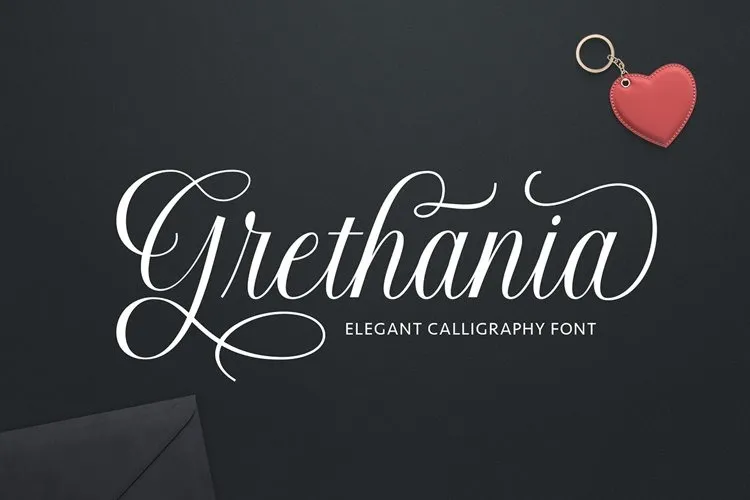
Grethania Font – Download Grátis
Grethania é uma nova fonte de corteleta elegante e moderna, perfeita para trabalhos formais que exigem tanto a elegância quanto a modernidade. Este script é um marco único no mundo das fuentes de calligrafia porque apresenta um estilo suave, limpo e feminino. Seu charme sensual e glamouroso faz com que seja uma escolha ideal para design em variados campos: desde cartões de convite e rótulos até logotipos, moda e estação de escrita; passando por românticas novelas, revistas e livros, cartões de congratulações ou casamentos e embalagens. A Grethania está concebida para se adaptar em qualquer situação formal do dia a dia, tornando-a uma fonte versátil que é perfeita tanto para designer profissionais quanto para criadores independentes desejosos de adicionar um toque sofisticado aos seus projetos.